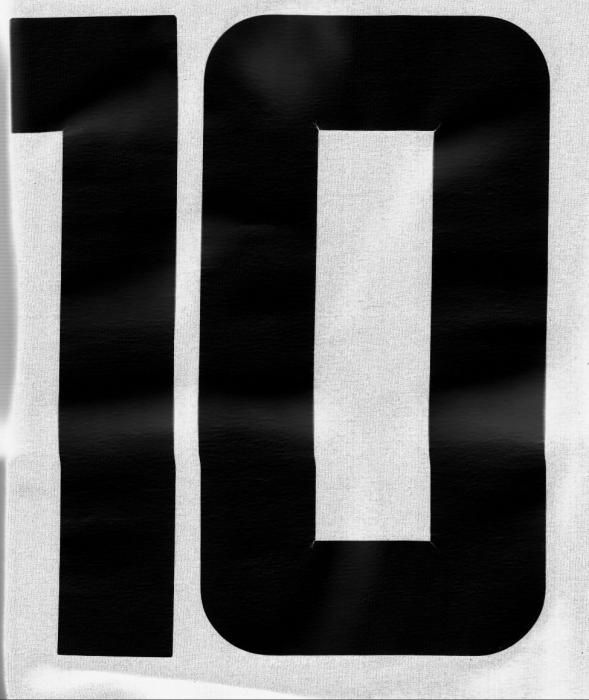
Suche Schriftart für eine Zahl
suche die Schriftart für folgende Zahl.
Meist passt nur die 1 oder die 0.
Bräuchte aber eine Schriftart mit beiden, da ich eine andere Zahl verwenden muss.
Für Trikots werden gern die Zahlen handgeschnitzt, damit sie optimal die verfügbare Fläche ausfüllen. Eine dazugehörige Satzschrift gibt es daher oft nicht.
Woher stammt dein Trikot? Vielleicht lassen sich darüber noch andere Zahlen finden …